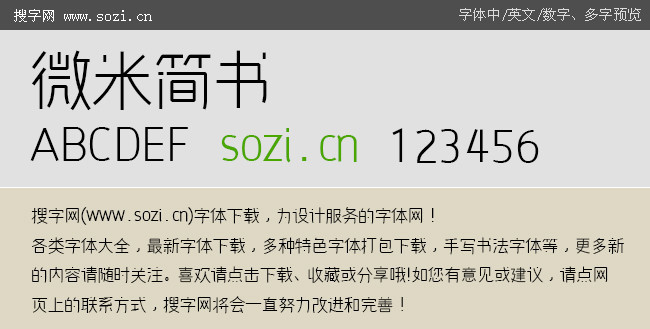
微米簡(jiǎn)書
搜字網(wǎng)給大家提供一款微米簡(jiǎn)書中文字體下載,微米簡(jiǎn)書字體是微米字庫中一款非常簡(jiǎn)單可愛的藝術(shù)字體,字體筆觸粗細(xì)適中,稚嫩可愛,具有很好的視覺感,適合應(yīng)用于藝術(shù)設(shè)計(jì)、平面宣傳設(shè)計(jì)、網(wǎng)頁設(shè)計(jì),書法字帖等領(lǐng)域。